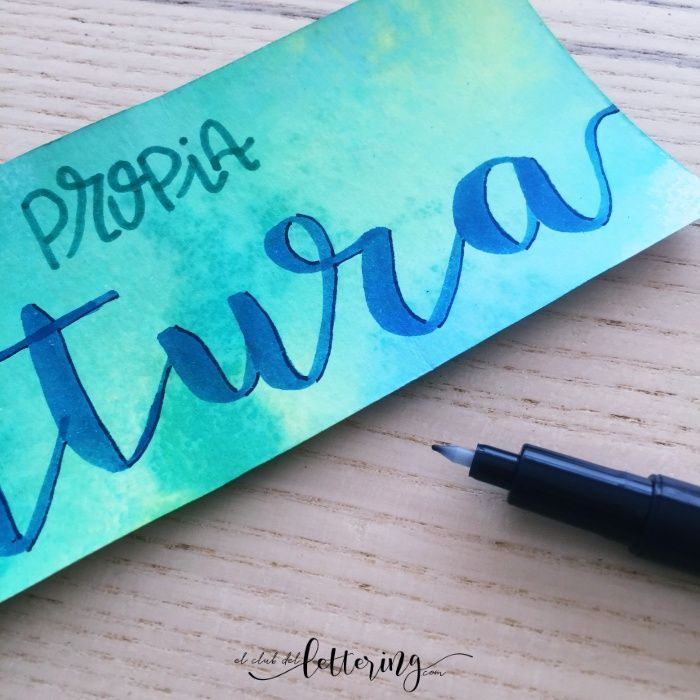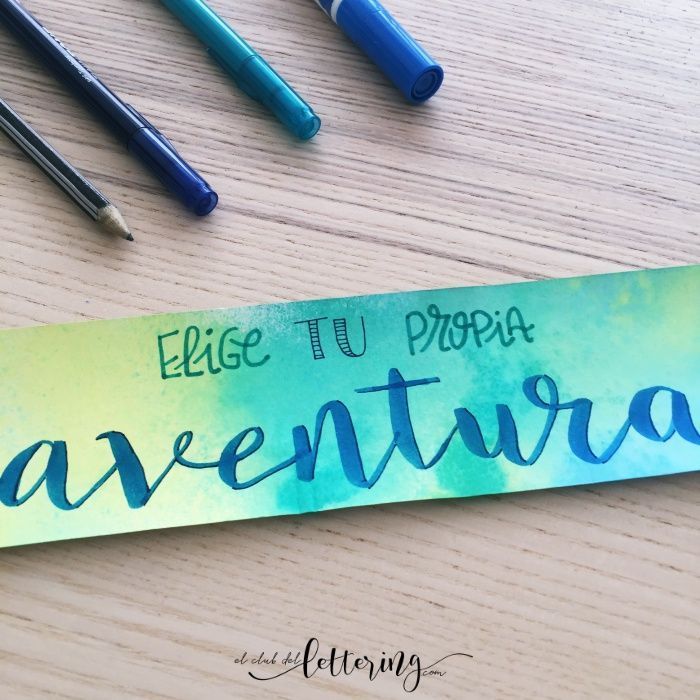
Marcador para libros con acuarelas y Lettering
Si te gusta aprender y vivir nuevas aventuras, seguramente te guste leer y tengas algún que otro libro entre manos.
Hoy te propongo que hagas tu propio punto de lectura para ese libro especial o para incluir como detalle personal cuando regales un libro.
Marcador para libros con acuarelas y Lettering
He preparado un tutorial paso a paso de cómo puedes hacer un marcador para libros personalizado con Lettering.
Marcador para libros con acuarelas y Lettering.
Para crear el fondo del marcador para libros tienes que pulverizar las acuarelas sobre el papel y dejar secar.
Verás que el papel se dobla al absorver el líquido. No te preocupes que al secarse, recuperará su forma.
Para acelerar el proceso de secado puedes ponerlo al sol o utilizar una pistola de calor.
Planifica tu Lettering
Mientras se va secando el marcador de páginas, vamos a aprovechar para planificar un poco cómo será nuestro Lettering.
Esta parte es muy importante para que el resultado de tu Lettering quede bien.
Lo primero es escribir en un papel las letras o texto que formarán tu Lettering.
Marca páginas con acuarelas y Lettering
Puedes probar y dibujar tu lettering en el papel sin marcarlo mucho y dejar las letras centradas, tal y como quieres que queden.
Marcador para libros con acuarelas y Lettering
Después, borra con la goma dejando las mínimas marcas para que puedas hacer tu lettering repasando por encima.
Para las letras del Lettering de la palabra principal he usado un rotulador Ecoline de color azul ultramar con punta de pincel.
He dibujado las letras trazo a trazo, para que queden bonitas con el efecto del brush lettering.
Marcador para libros con acuarelas y Lettering
Es el momento de añadir la otra parte del lettering.
En esta ocasión, vamos a combinar letras mayúsculas y minúsculas en la parte superior.
Usamos de nuevo el lápiz para ver cómo queda antes de dibujarlo con rotuladores.
Repasamos con los rotuladores de colores y borramos el lápiz.
Para estas letras, he usado los Rotuladore Twintone de Tombow y hemos combinado la punta  redonda más gordita y la más fina.
Por último, y utilizando el mismo rotulador que antes, he añadido unos trazos de color azul oscuro a modo de sombra.
Y así ha quedado finalmente mi marcador para libros hecho con el fondo de acuarela y lettering. ¿Está chulo verdad? A mí me encanta :).
Para el lettering puedes usar frases que te gusten, una dedicatoria si lo vas a regalar o también escribir una poesía.
Por si te sirven de inspiración, te dejo aquí algunas frases que puedes usar para el lettering de tu marcapáginas.
• Leer mola.
• Una página más y a dormir.
• Leer es una gran aventura.
• Por aquí me quedé.
• Para viajar lejos, no hay mejor nave que un libro.